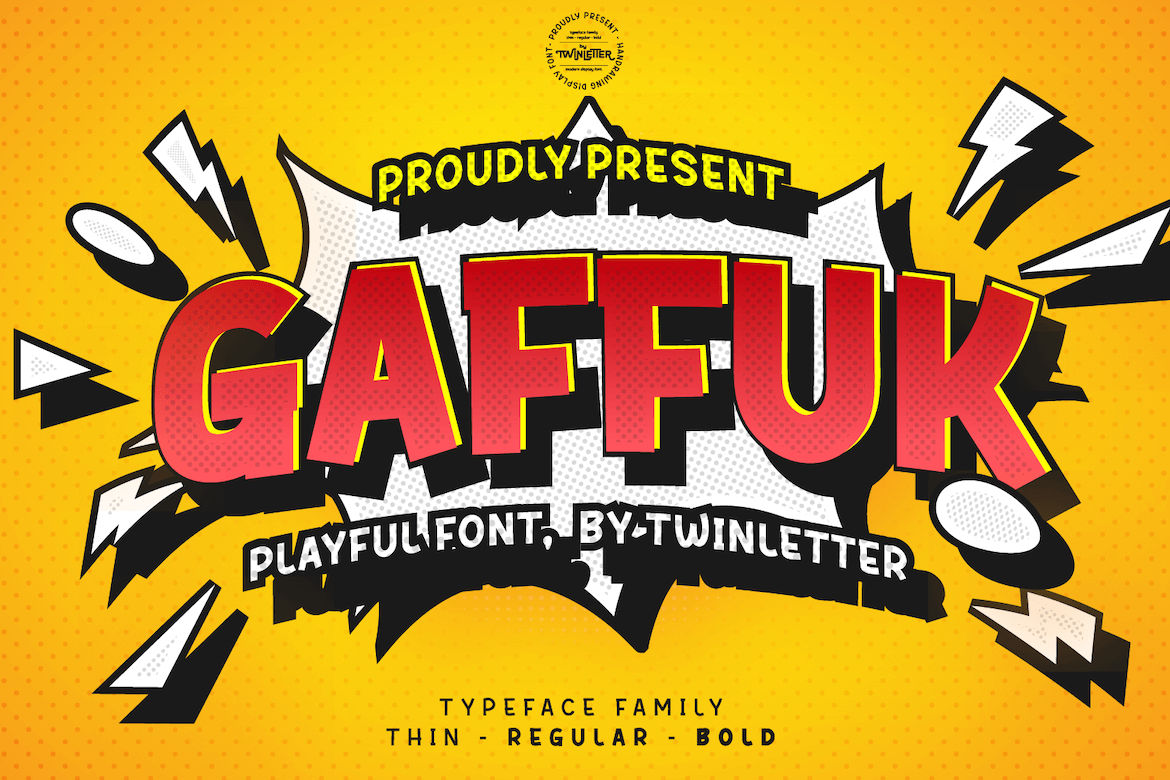
Aqui está uma breve descrição para a página de download da font ‘Gaffuk Font’: Esta ‘Gaffuk Font’ é perfeita para quem busca um estilo moderno e bold, com um toque único e divertido. A sua tipografia espessa e cheia de personalidade criará designs que chamam atenção instantaneamente. Se você está procurando por uma fonte que combine a estética moderna dos títulos grandes e o charme peculiar das fonts expressivas, essa é definitivamente uma escolha brilhante para adicionar à sua coleção. Não apenas adequada para os logos de marcas e as etiquetas de embalagem, ‘Gaffuk Font’ também se destaca no design gráfico, seja em revistas, logotipos ou até mesmo nos cartões-postais. A fonte está disponível para download do twinletter designer, oferecendo uma maneira criativa de tornar seus projetos ainda mais distintivos e atraentes.